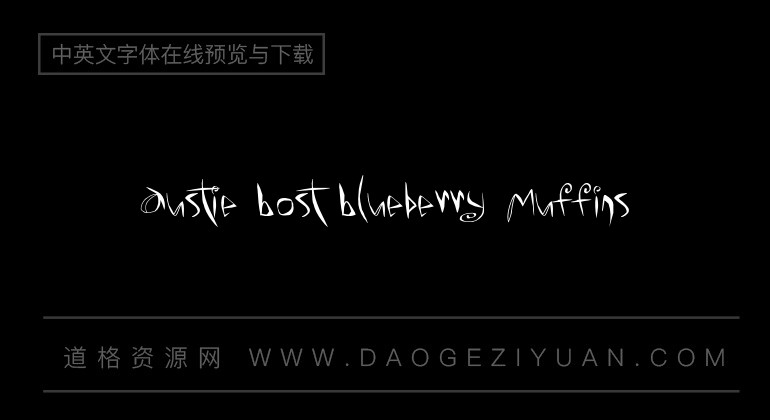
Austie Bost Blueberry Muffins 字体是一款由 Austie Bost 设计的可爱、温暖、舒适的手写字体。它拥有自然的流动性,适用于各种类型的设计,尤其适合用于插画、卡通、婚礼、海报、品牌标识等等。它的字体风格清新、温暖,可以让你的设计更加有灵气。内容介绍
Austie Bost Blueberry Muffins是一款非常不错的手写艺术字体,具有很好的视觉感,适合于文化类的宣传设计、商业类品牌的广告和产品包装设计以及个性化文字排版等较多场景。